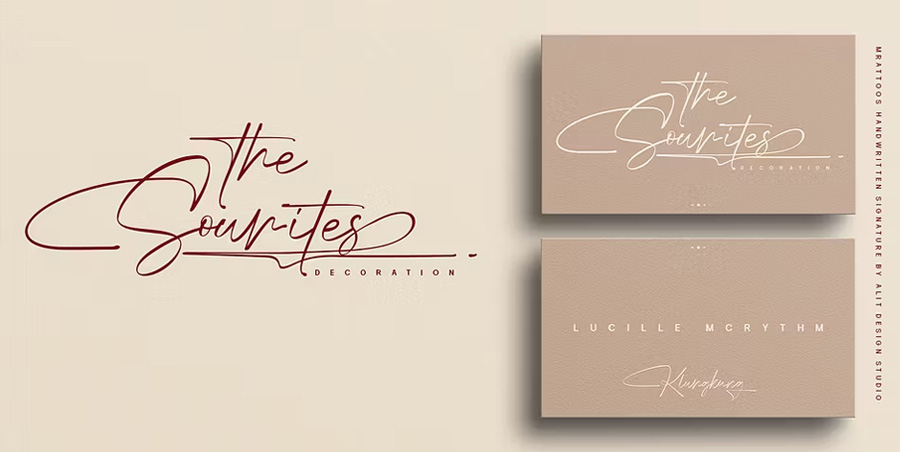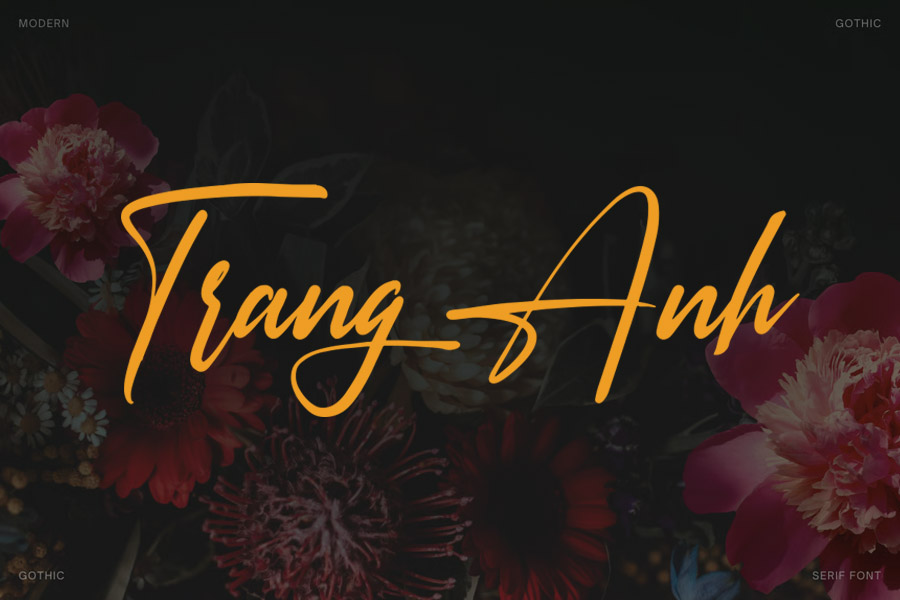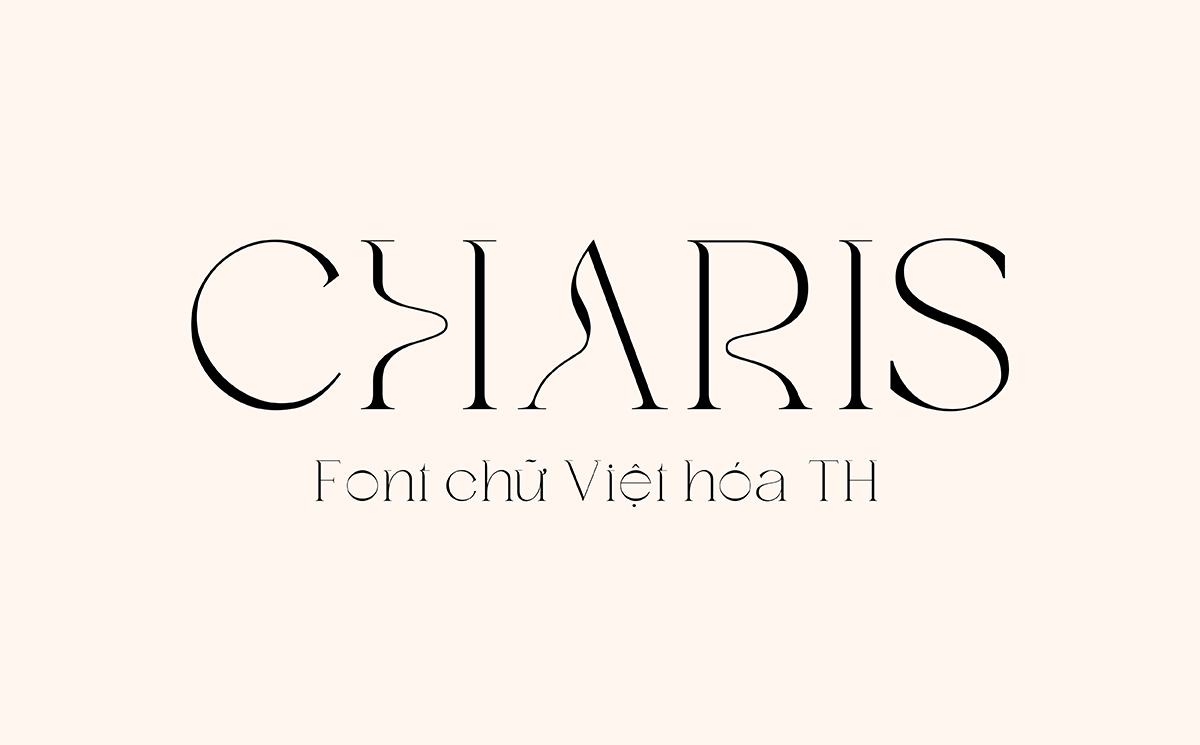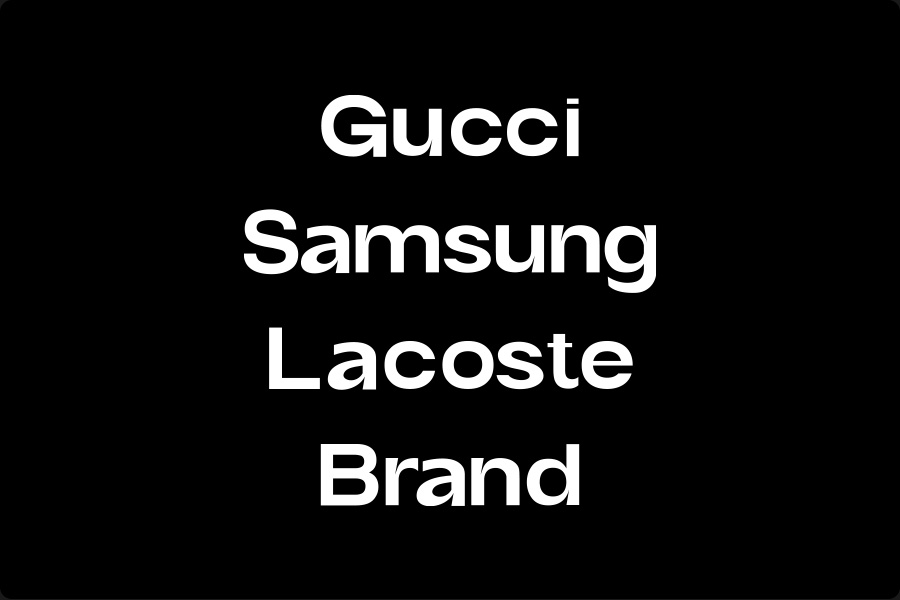
[Tải Xuống] Top 16 Font Chữ Spa Việt Hóa Đẹp Nhất 2025 Cho Lĩnh Vực Làm Đẹp, Thẩm Mỹ
Tuyển chọn 16 font chữ spa Việt hóa đẹp, mềm mại và chuyên nghiệp – lý tưởng cho logo, menu, bảng hiệu và ấn phẩm thương hiệu spa năm 2025.
Khi bạn bước vào một spa, điều gì khiến bạn thấy thư giãn đầu tiên? Có thể là mùi tinh dầu, âm nhạc nhẹ nhàng, hay chính là cách bài trí tổng thể – trong đó có cả... font chữ trên bảng hiệu, tờ rơi hay menu.
Ít ai để ý, nhưng font chữ đóng vai trò không nhỏ trong việc truyền tải tinh thần của thương hiệu spa – từ sự mềm mại, nữ tính đến cảm giác cao cấp và chuyên nghiệp.
Nếu bạn là designer, marketer hay chủ spa, đang tìm kiếm font chữ spa Việt hóa đẹp, hỗ trợ đầy đủ tiếng Việt, dễ dùng và thể hiện đúng phong cách dịch vụ, thì danh sách dưới đây chính là dành cho bạn.
Cùng Fontdep.vn khám phá Top 16 font chữ spa Việt hóa đẹp nhất 2025, được tuyển chọn kỹ lưỡng, phù hợp với mọi nhu cầu: từ logo, bảng giá đến poster, website và ấn phẩm truyền thông.
Font chữ Spa là gì? Vì sao quan trọng trong thiết kế thương hiệu làm đẹp?
Font chữ Spa là kiểu chữ được sử dụng trong các thiết kế liên quan đến lĩnh vực spa, thẩm mỹ viện, chăm sóc sắc đẹp. Các font này thường mang phong cách mềm mại, tinh tế và thư giãn, giúp truyền tải đúng cảm xúc và hình ảnh mà thương hiệu Spa muốn thể hiện.
Trong thiết kế thương hiệu làm đẹp, font chữ không chỉ là yếu tố trang trí mà còn là ngôn ngữ thị giác, thể hiện rõ:
- Phong cách dịch vụ (cao cấp, thiên nhiên, hiện đại...)
- Trải nghiệm khách hàng muốn hướng đến (thư giãn, sang trọng, thân thiện)
- Tính đồng bộ trong toàn bộ hệ thống nhận diện (logo, bảng giá, website, mạng xã hội...)
Khi thị trường spa ngày càng cạnh tranh, việc sử dụng đúng phông chữ Spa Việt hóa đẹp và chuyên nghiệp sẽ giúp thương hiệu:
- Tăng tính nhận diện
- Tạo cảm xúc thị giác tích cực
- Gây ấn tượng với khách hàng ngay từ ánh nhìn đầu tiên
Tiêu chí chọn font Spa chất lượng
- Hỗ trợ tiếng Việt: Đầy đủ dấu, không lỗi font
- Dễ đọc & thẩm mỹ: In ấn tốt, đồ hiển tốt trên mọi nền
- Phong cách đồng nhất: Phù hợp concept Spa (thiên nhiên, cao cấp, Hàn Quốc...)
- Đúng mục đích: Phù hợp logo, social media, in ấn hay quảng cáo
Top 16 Font Chữ Spa Việt Hóa Đẹp Nhất 2025
Kiểu Viết Tay Mềm Mại – Gần Gũi, Bay Bổng, Cá Tính
Font chữ script và handwritten thường mang lại cảm giác thân thiện, lãng mạn hoặc cá nhân hóa, rất phù hợp cho thiết kế logo, bảng hiệu hoặc thiệp mời trong ngành spa. Những nét chữ mềm mại, bay bổng giúp tạo nên sự kết nối cảm xúc nhẹ nhàng với khách hàng.
TH Mrattoos Regular – Mềm mại & Thanh lịch
TH Mrattoos Regular là một font viết tay mô phỏng nét chữ ký mềm mại, có sự uyển chuyển tự nhiên giữa các ký tự. Font mang phong cách hiện đại, đường nét uốn lượn và có độ tương phản nhẹ giữa nét thanh và nét đậm, tạo nên cảm giác gần gũi, cao cấp và mang tính cá nhân cao. Khoảng cách chữ đều, dễ nhìn, phù hợp cho thiết kế logo spa, tiêu đề, danh thiếp hoặc thiệp mời mang phong cách thanh lịch, tinh tế.
Tác giả gốc: Alit Suarnegara, một nhà thiết kế đến từ Indonesia, thuộc studio nổi tiếng Alit Design.
Việt hóa bởi: Phạm Sơn - Admin S99, Fontdep.vn
SVN Rosellinda Alyamore – Bay bổng & Lãng mạn
SVN Rosellinda Alyamore là font chữ viết tay mang đậm tính nghệ thuật, các chữ cái được nối liền bằng nét mềm mượt, uốn cong nhẹ nhàng. Phong cách chữ gợi liên tưởng đến thư pháp hiện đại, bay bổng và lãng mạn, thích hợp với các thiết kế spa thiên nhiên, mỹ phẩm nữ tính hoặc thiệp mời. Font hỗ trợ nhiều ký tự thay thế, giúp thể hiện sự cá nhân hóa và nghệ thuật trong từng thiết kế.
Tác giả gốc: Hanief Farandi thuộc Hanzel Space Studio.
Việt hóa bởi: STYLEno.1
TH Maistoray – Tự do & Linh hoạt
TH Maistoray mang đến phong cách chữ ký cá nhân đầy tự do với các nét chữ kéo dài, có độ nghiêng nhẹ và nhấn nhá ở những điểm kết thúc. Font mang đậm hơi hướng hiện đại, thanh thoát và linh hoạt, phù hợp với logo, bảng hiệu hoặc các thiết kế spa mang phong cách chuyên nghiệp nhưng vẫn giữ được vẻ mềm mại, thân thiện. Font giữ cấu trúc dễ đọc và không quá cầu kỳ.
Tác giả gốc: Gilang Maulana, thuộc studio Maulana Creative
Việt hóa bởi: Phạm Sơn - Admin S99, Fontdep.vn
TH Rieldstomy Madison – Mộc mạc & Tự nhiên
Font TH Rieldstomy Madison thuộc dòng brush script, mô phỏng nét viết bằng bút lông mềm. Đường nét mềm mại, có độ rung nhẹ tạo hiệu ứng thủ công, nhưng vẫn giữ được sự thanh thoát và nhất quán trong tổng thể. Rất lý tưởng cho các thiết kế poster, bảng hiệu, bao bì spa hoặc dịch vụ làm đẹp có yếu tố nghệ thuật và tự nhiên.
Tác giả gốc: Glorytype Studio
Việt hóa bởi: Phạm Sơn - Admin S99, Fontdep.vn
TH Molahesta – Cổ điển & Duyên dáng
TH Molahesta mang phong cách cursive cổ điển, với các nét nghiêng đều và bo tròn mượt mà. Kiểu chữ này tạo cảm giác thư giãn, nhẹ nhàng và rất nữ tính – rất phù hợp cho thiết kế spa handmade, dịch vụ dưỡng sinh hoặc chăm sóc da. Các ký tự được cách điệu vừa đủ để tạo sự duyên dáng mà không làm mất đi tính dễ đọc.
Chọn đúng font chữ spa không chỉ giúp thiết kế đẹp hơn, mà còn giúp khách hàng cảm nhận được phong cách và chất lượng dịch vụ ngay từ cái nhìn đầu tiên. Hy vọng với danh sách 16 font spa Việt hóa ở trên, bạn đã tìm được những cái tên lý tưởng cho dự án của mình – từ logo, bảng hiệu đến menu hay ấn phẩm truyền thông.